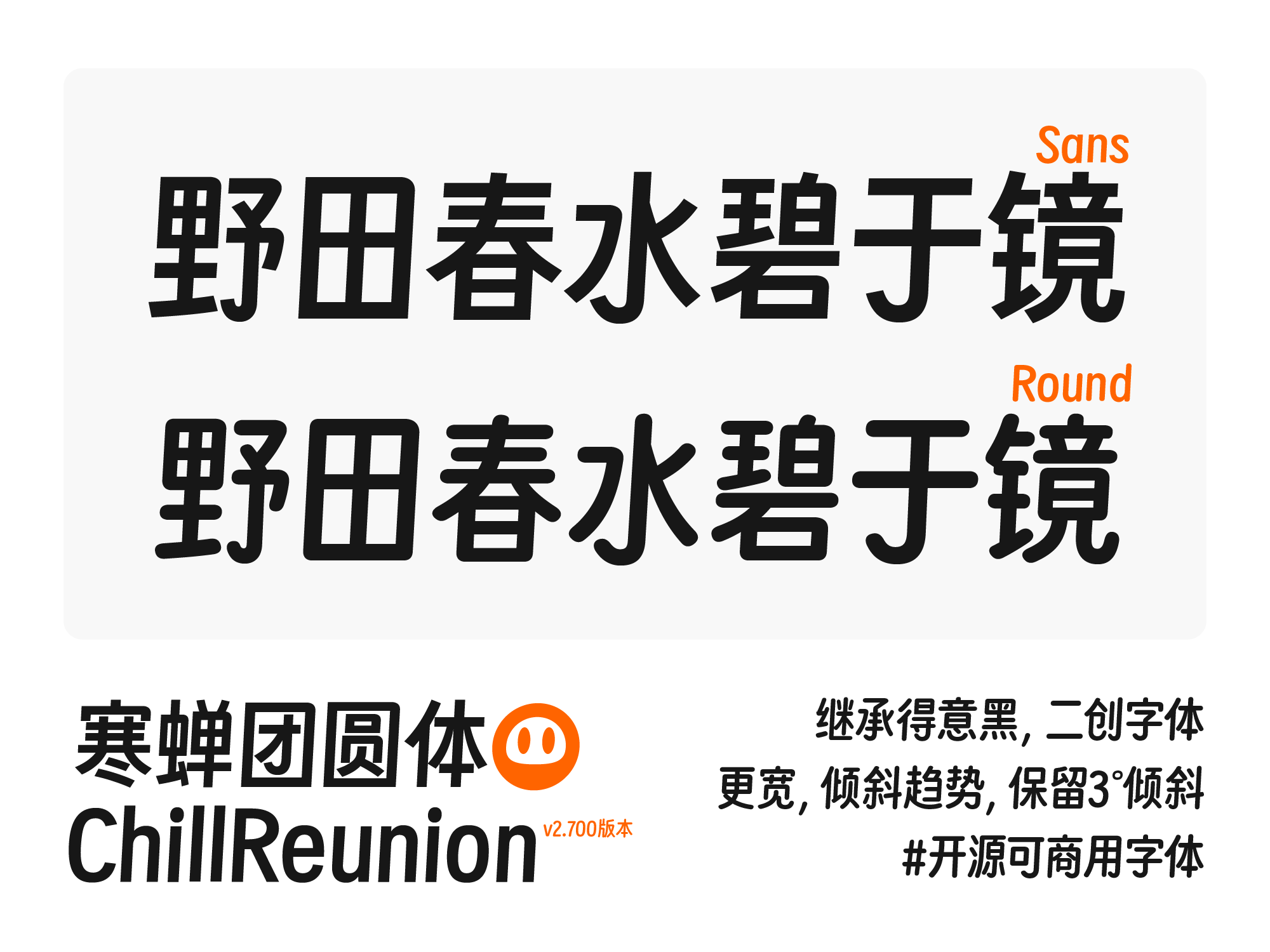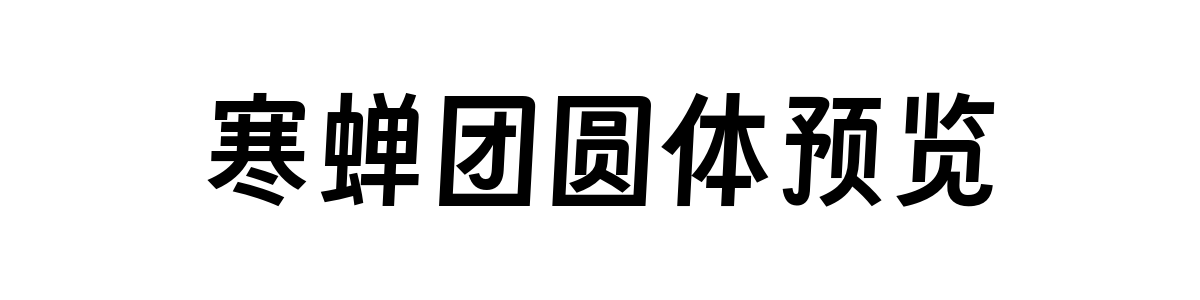
寒蝉团圆体
寒蝉团圆体(Chill Reunion)是一款基于开源字体得意黑进行二次创作,在得意黑坚实、现代的黑体骨架基础上,将整套字库倾斜角度修改为3°,形成稳定且具有动感的统一视觉趋势。除倾斜调整外,字体还新增了部分实用字符,并对竖排排版特性进行了专门优化,提升了在传统竖版书写场景下的兼容性与美观度。
字体风格
寒蝉团圆体并非模仿手写速度感的随意倾斜,修改倾斜角度为3°,产生了一种向右上方微微跃升的视觉趋势,如同整齐划一的队列迈出轻盈的步伐。尽管具有倾斜角度,但其所有字符的倾斜轴线和曲率变化都保持着高度的一致性,展现出一种“理性的活泼”。